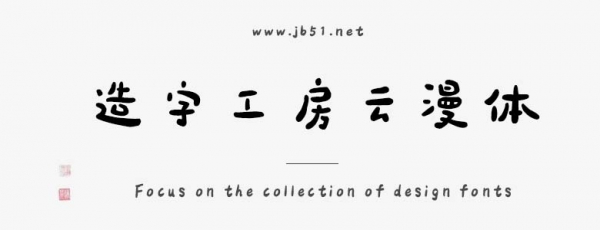
造字工房云漫體由上首造字字庫(kù)出品的字體,整體字形圓潤(rùn),結(jié)構(gòu)疏朗,筆畫(huà)富有彈性,提升了字體的呼吸感和通透性,弧度錯(cuò)落明快,規(guī)避視覺(jué)上的呆板,給人以靈動(dòng)松散的視覺(jué)體驗(yàn)。適合應(yīng)用于平面宣傳設(shè)計(jì)、網(wǎng)頁(yè)設(shè)計(jì),書(shū)法字帖等領(lǐng)域,需要的朋友可以前來(lái)本站下載。
云漫體是一款輕松可愛(ài)、古靈精怪的全新手寫(xiě)字體,其活潑跳脫的風(fēng)格十分符合當(dāng)代人的審美需求。整體字形圓潤(rùn),結(jié)構(gòu)疏朗,筆畫(huà)富有彈性,提升了字體的呼吸感和通透性,弧度錯(cuò)落明快,規(guī)避視覺(jué)上的呆板,給人以靈動(dòng)松散的視覺(jué)體驗(yàn)。本字體為簡(jiǎn)體字庫(kù),采用OpenType/CID格式,Adobe-GB1-5編碼?;谥腥A人民共和國(guó)GB2312-80字符集標(biāo)準(zhǔn),另按需添加101個(gè)漢字。共收容字?jǐn)?shù)6864CJK漢字,ASCII常用字符100個(gè)。